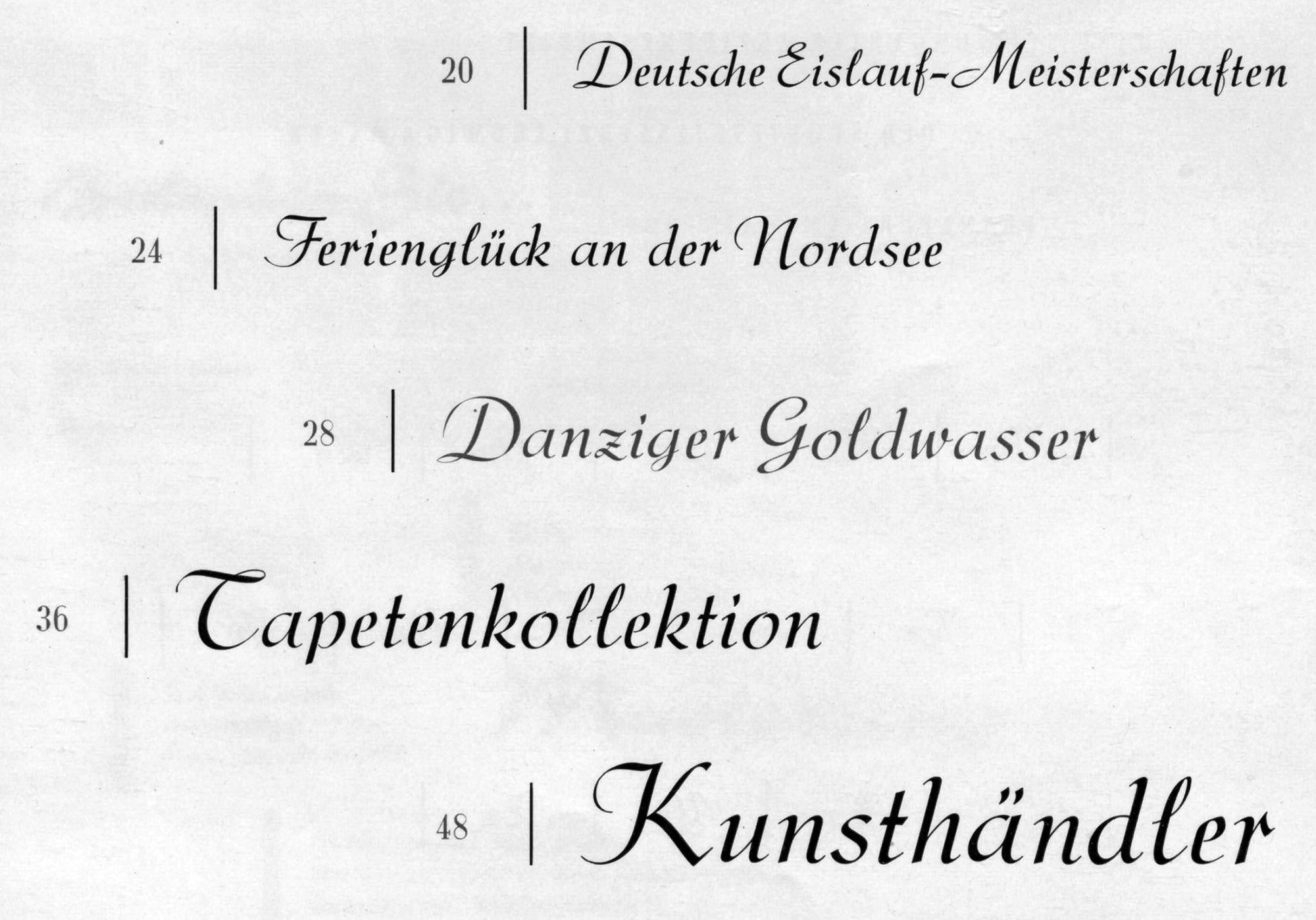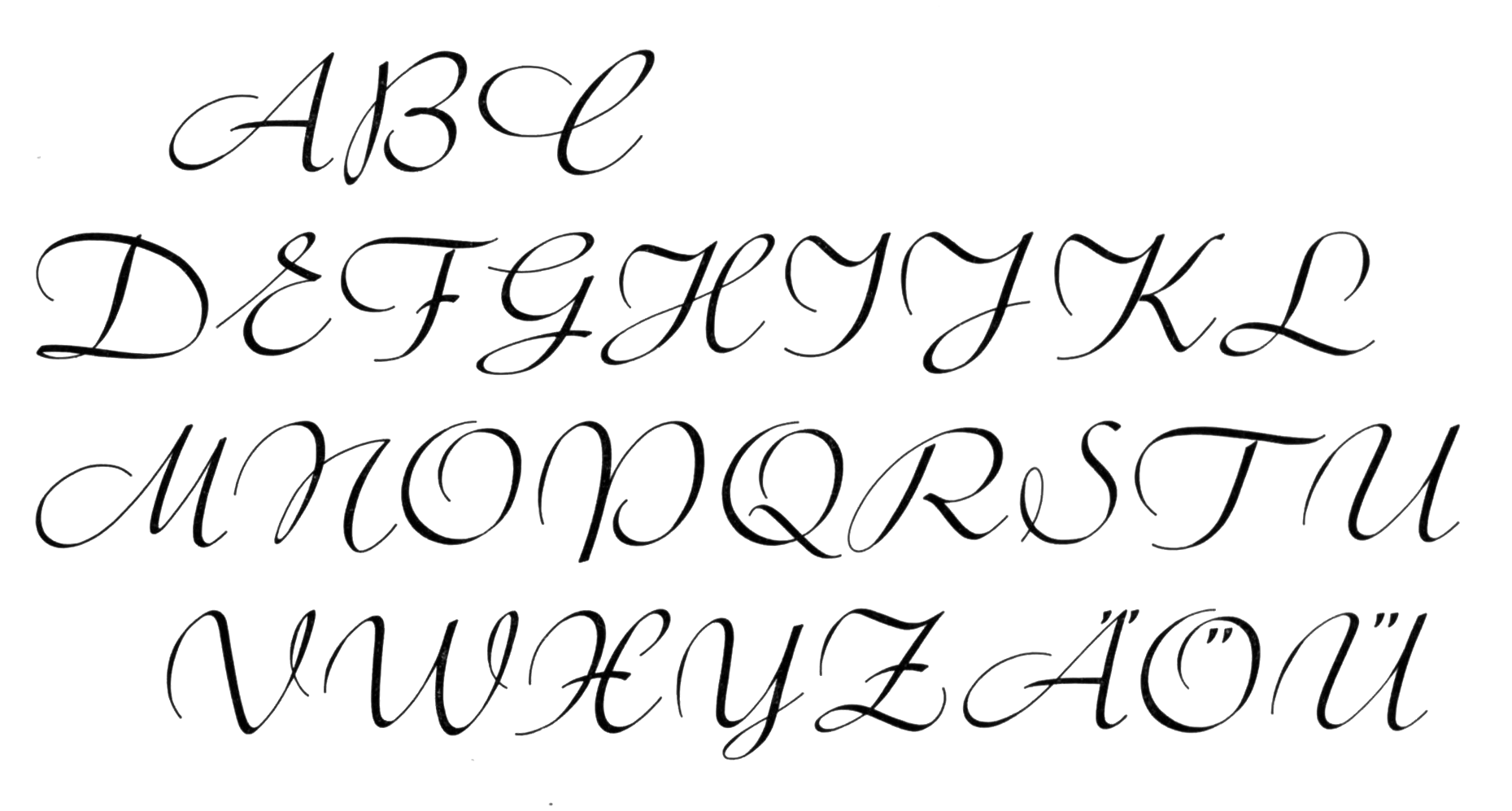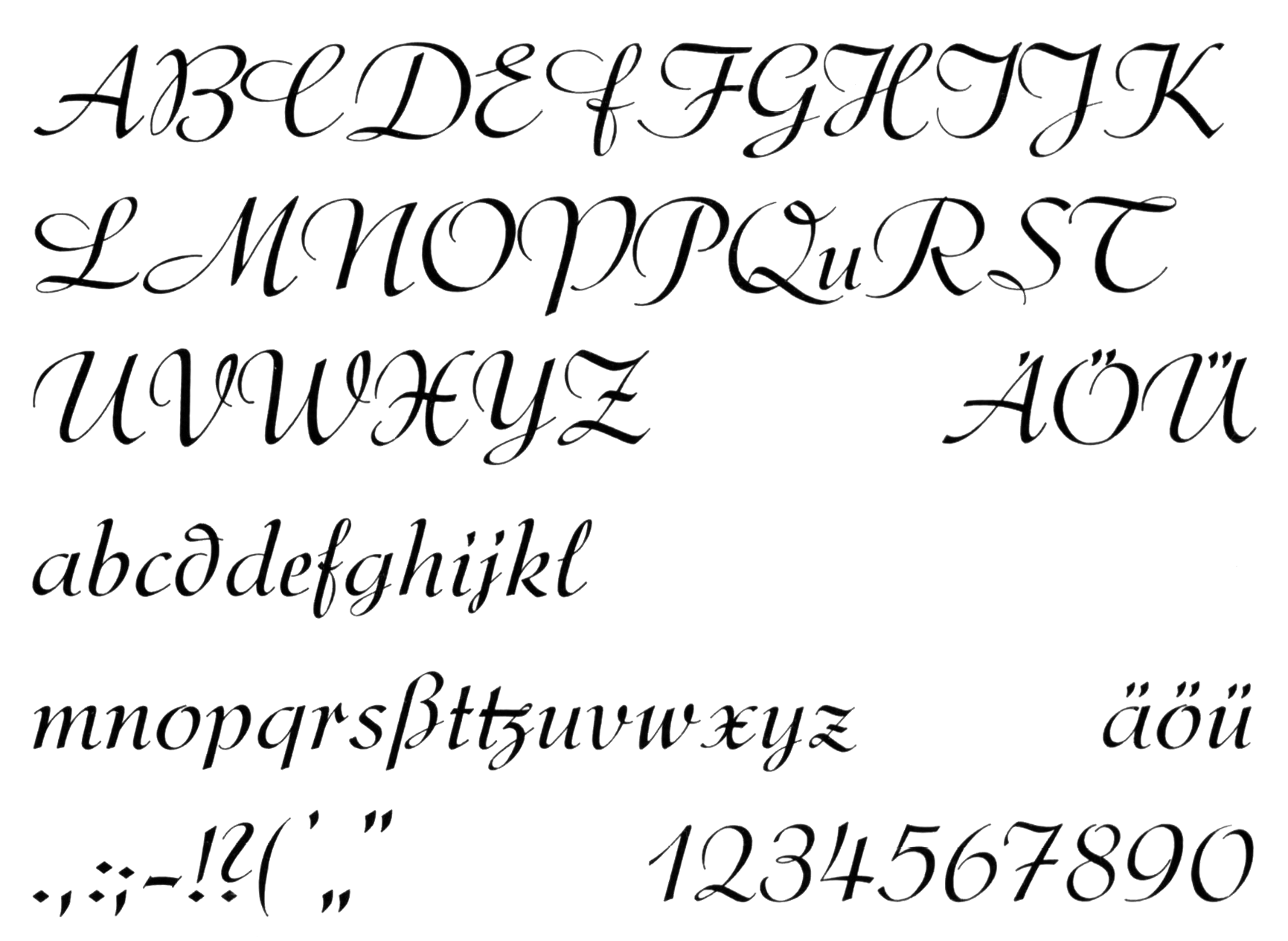
Die Skizze ist eine unverbundene Schreibschrift von Walter Höhnisch und erschien in den 1930er-Jahren bei Ludwig & Mayer mit zugehörigen Schwungbuchstaben. Schriftguss in Dresden bot die Schrift später unter dem Namen Diva an.
Eine Digitalisierung gibt es als RMU Skizze von RMU Fonts.
Bleisatz-Figurenverzeichnis
Schwungbuchstaben